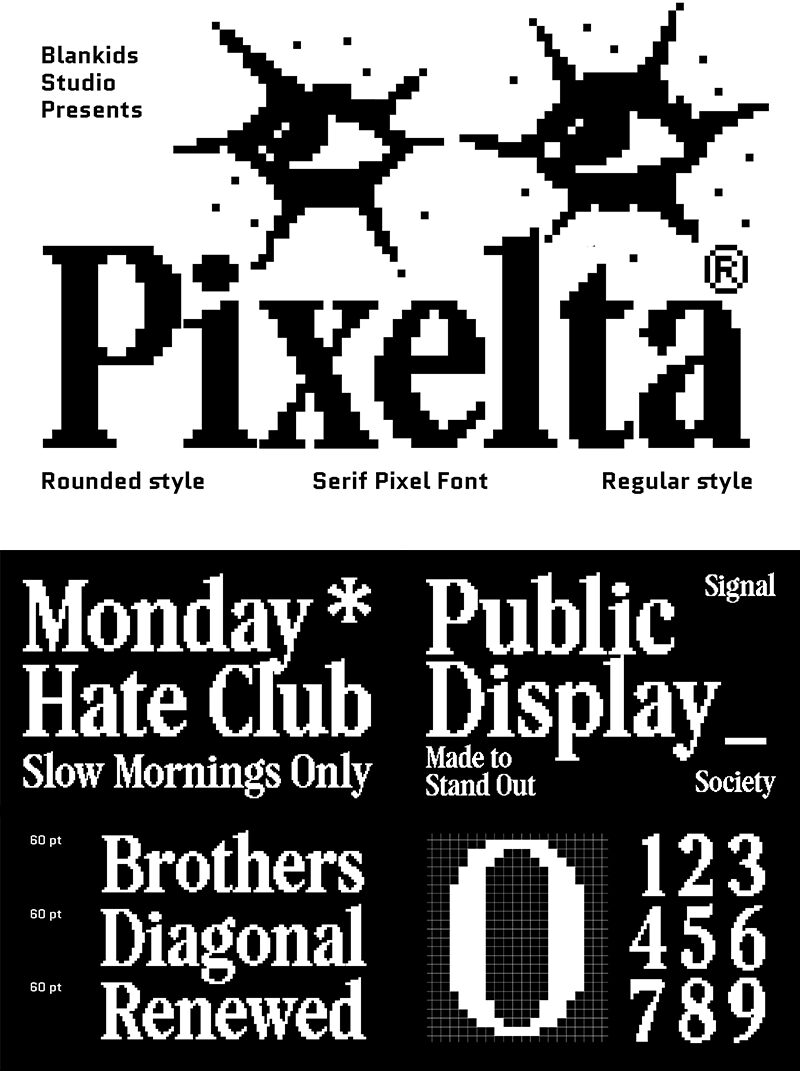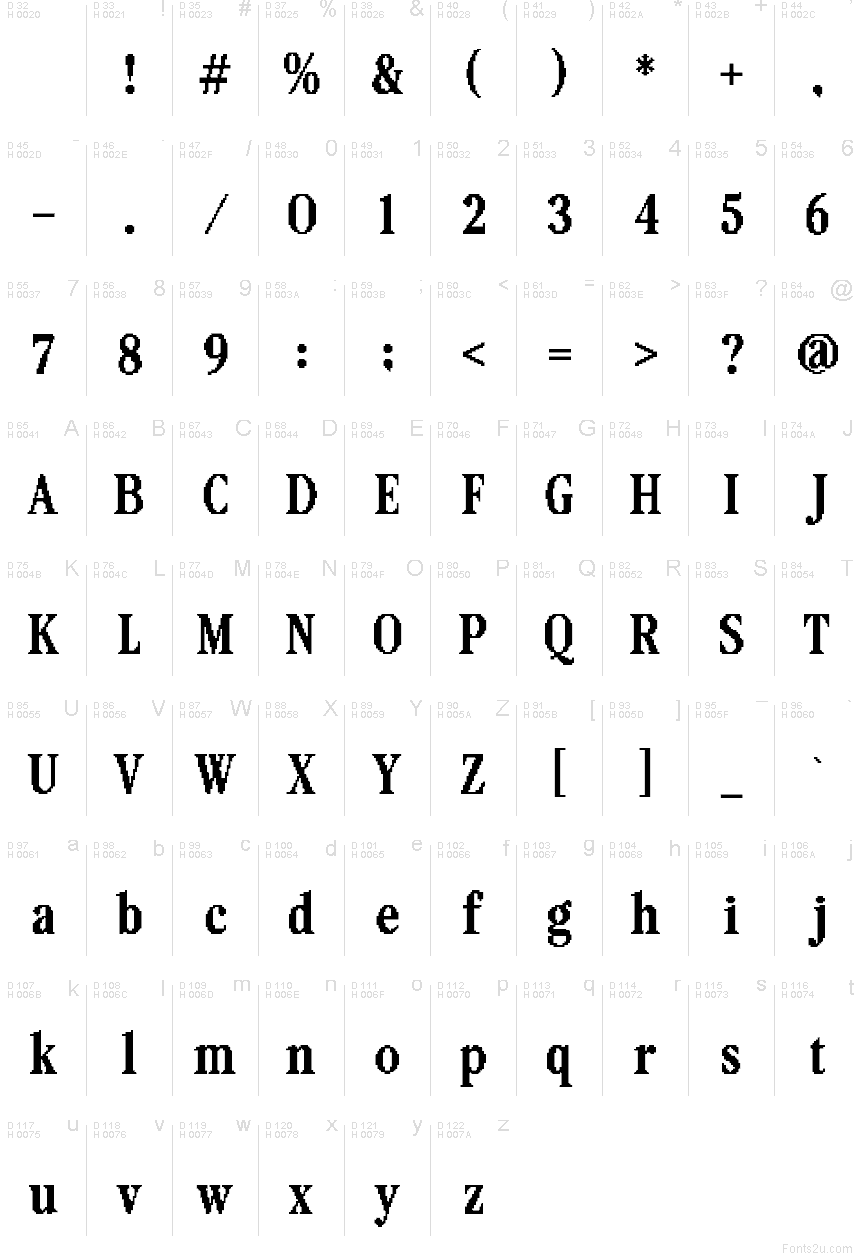
Pixelta Regular Písmo
Pixelta od studia Blankids Studio, vytvořené v roce 2026, je bezplatné pixelové písmo s vysokými, těsně vysázenými literami a nečekaně formální siluetou. Výrazné svislé tahy se setkávají s ostrými detaily připomínajícími patky, což designu propůjčuje ráz starého novinového písma převedeného do nízkého rozlišení. Užší tvary minusek udržují celkovou kresbu textu živou a pestrou.
Retro computing a arkádová tematika nabízejí přirozené prostředí pro herní rozhraní, plakáty elektronické hudby a technologický merch. Titulní obrazovky her jsou jeho nejpřesvědčivější rolí.